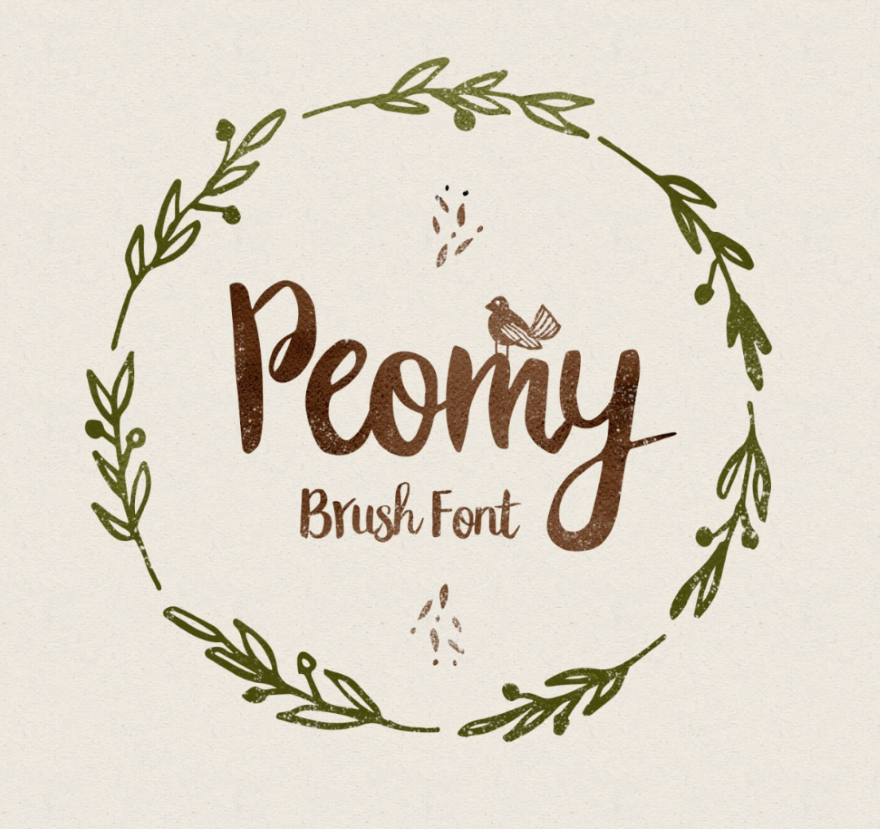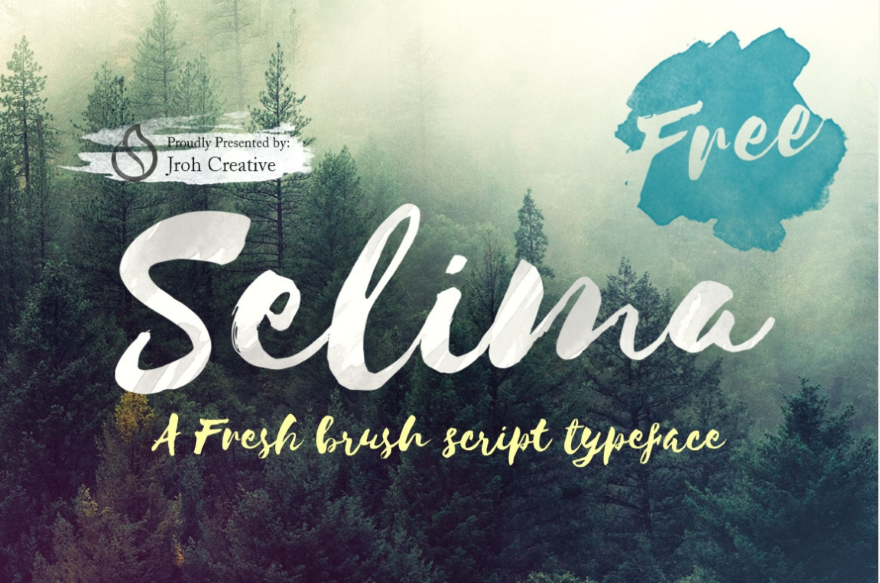
22 шрифта кистью, чтобы добавить рисованный элемент в ваш дизайн
Опубликовано: 2018-12-05В Интернете можно выбирать из множества шрифтов в самых разных дизайнах. Один дизайн, который меня привлекает, - это шрифт кисти. Этот дизайн шрифта имеет художественный элемент, который выделяется независимо от того, насколько простой или сложный дизайн шрифта. В этой статье мы рассмотрим 22 шрифта кисти, чтобы добавить элемент, нарисованный вручную, в ваш дизайн.
1. Атмосфера
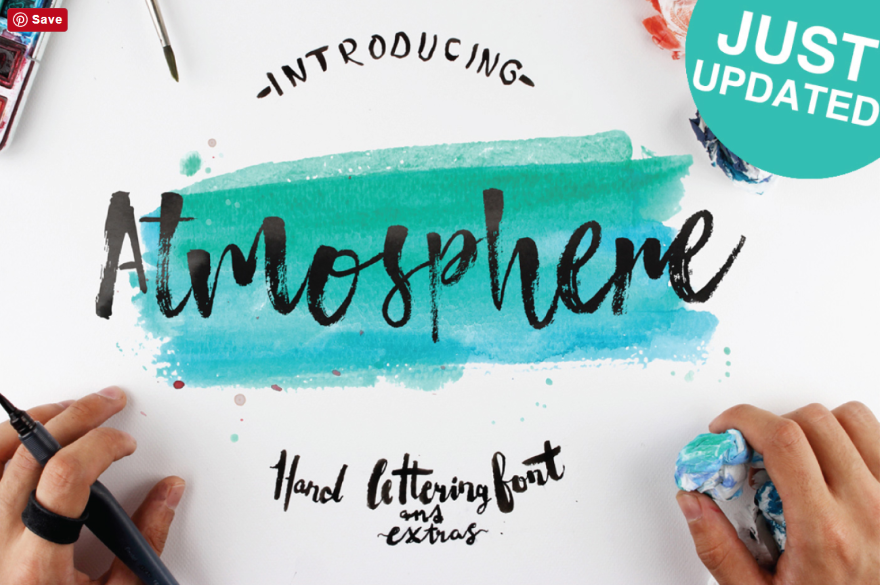
Атмосфера - это нарисованный вручную шрифт с естественными мазками кисти для создания аутентичной текстуры кисти. Он включает символы верхнего и нижнего регистра, цифры, знаки препинания и символы. Он также поставляется с 20 акварельными пятнами, которые можно использовать в ваших типографских работах. Это бесплатно для личного и коммерческого использования.
2. Банауэ расширенный
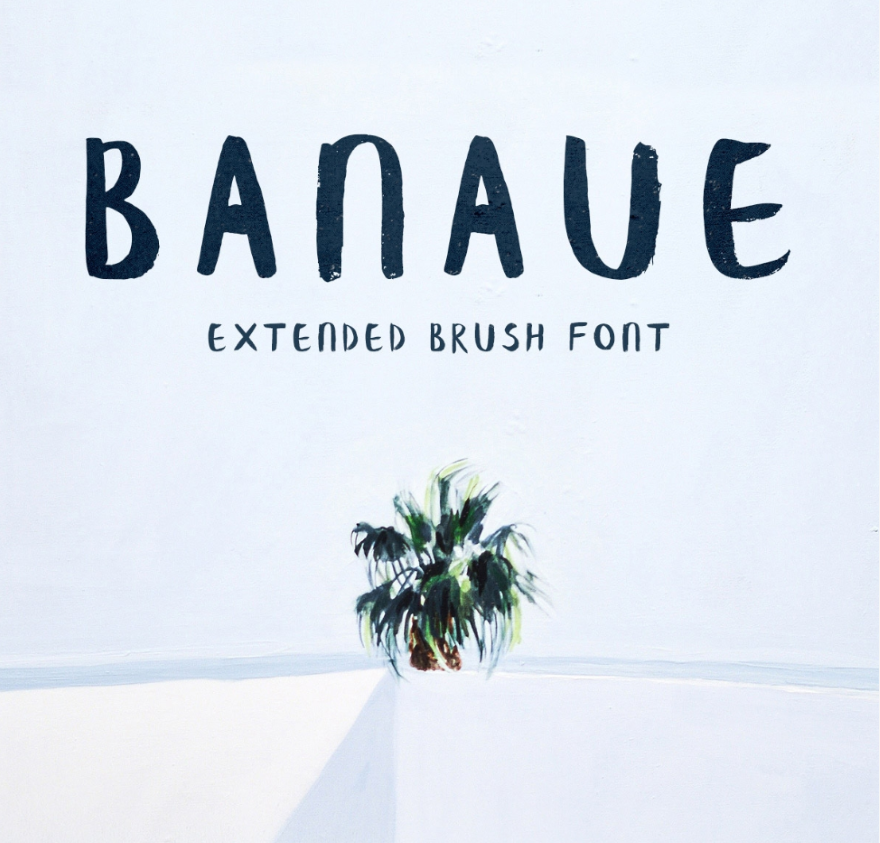
Banaue Extended - это премиум-версия бесплатного шрифта Banaue. Он содержит 329 символов, включая прописные и строчные буквы, цифры, символы, кириллические буквы и глифы для стран ЕС. Он включает символы для семи языков. Есть несколько лицензий на выбор.
3. Бесом
Бэсом был нарисован вручную кистью, напоминающей сырой веник. Он имеет расширенную латинскую букву, 156 символов, а бесплатная версия включает только прописные буквы. Расширенная расширенная версия премиум-класса включает глифы, расширенную базу символов кириллицы и латиницы и строчные буквы.
4. Blusty
Blusty - это дуэт рукописных шрифтов с без засечек и скриптового шрифта, основанного на реальном почерке. Он включает прописные и строчные буквы, стилистические варианты, стандартные лигатуры, числа, знаки препинания и акценты для многоязычных символов. Его можно использовать для неограниченного количества личных или коммерческих проектов, а также для неограниченных продаж конечных продуктов.
5. Брукс
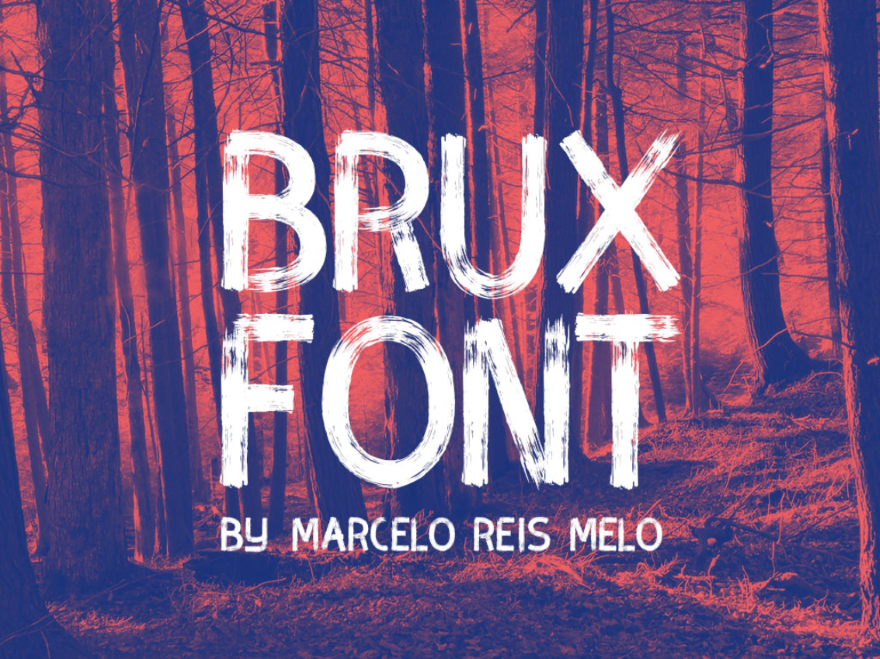
Brux - это шрифт кисти с толстыми мазками и имитация сухой кисти. Он включает английские, немецкие и испанские символы заглавными буквами. Он также включает числа, знаки препинания и символы. Используйте его для личного или коммерческого использования.
6. Дебби
Debby - это рисованный кистью шрифт, который выглядит естественно с его нерегулярными упругими символами и грубыми формами. Он включает прописные и строчные буквы, цифры, знаки препинания и символы.
7. Кисть мечтателей
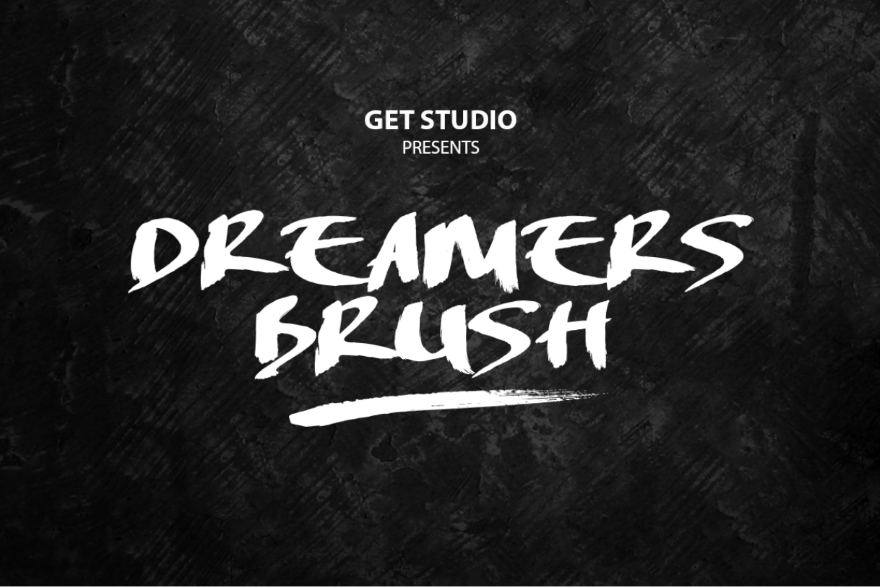
Dreamers Brush - это шрифт ручной работы, созданный для создания рукописного вида. Он включает буквы верхнего и нижнего регистра, цифры, знаки препинания и символы.
8. Эматоды
Ematodas - это смелый рукописный шрифт с текстурой сухой кисти. Он включает прописные и строчные буквы, цифры, знаки препинания, символы, лигатуры и стилистические варианты. Его можно использовать для неограниченного количества личных или коммерческих проектов, а также для неограниченных продаж конечных продуктов.
9. Кисть для козьей кожи.
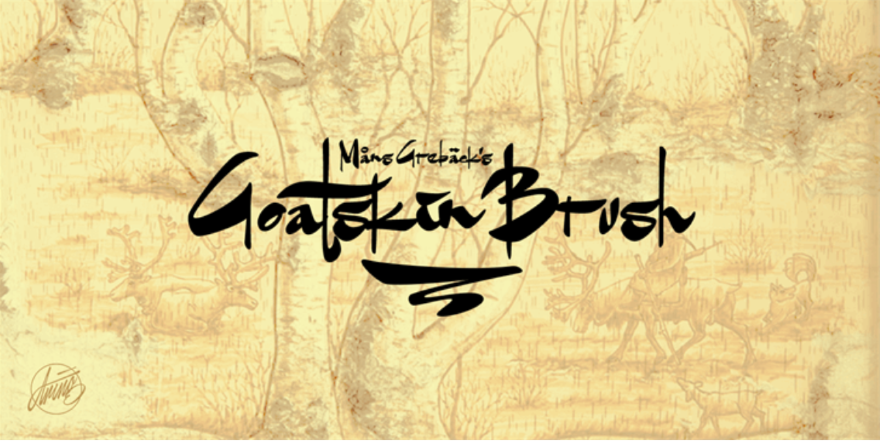
Goatskin Brush - это шрифт кисти в азиатском стиле. У него есть как толстые, так и тонкие мазки. Он включает буквы верхнего и нижнего регистра, знаки препинания и символы. Есть бесплатная версия для некоммерческого использования и множество лицензий на выбор.
10. Хенса
Hensa - это нарисованный вручную шрифт скрипта кисти, который включает прописные и строчные буквы, знаки препинания, числа и лигатуры. Также есть несколько штрихов. Этот выглядит особенно интересно, когда буквы имеют различное количество чернил.
11. Жимолость.
Honeysuckle - веселый и симпатичный шрифт-кисть, в котором по умолчанию используются буквы, альтернативные буквы, знаки препинания, числа и многоязычная поддержка. Он также включает дополнительные штрихи и декоративные элементы для создания причудливых линий. Его можно использовать в неограниченном количестве коммерческих проектов, включая продажу готовой продукции.
12. Kust Extended
Kust Extended - это премиум-версия бесплатного шрифта Kust. Это рукописный шрифт, который был нарисован на твердой бумаге толстой кистью с использованием чистых черных чернил, чтобы каждая буква выглядела искаженно. Он включает 430 символов с прописными и строчными буквами, цифры, знаки препинания, символы, латиницу, кириллицу и многое другое.
Кистевые шрифты имеют интересный дизайн, и я заметил, что они привлекают мое внимание. Они отлично подходят для логотипов, плакатов, печатных материалов, заголовков, баннеров, рекламы и многого другого. Независимо от того, для чего вам нужны кистевые шрифты, вы обязательно найдете в этом списке что-то, что идеально подходит для вашего проекта.